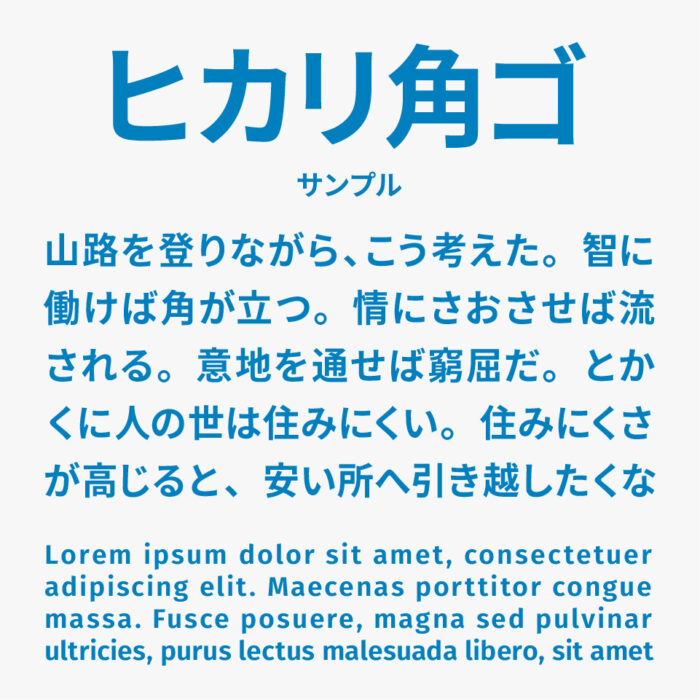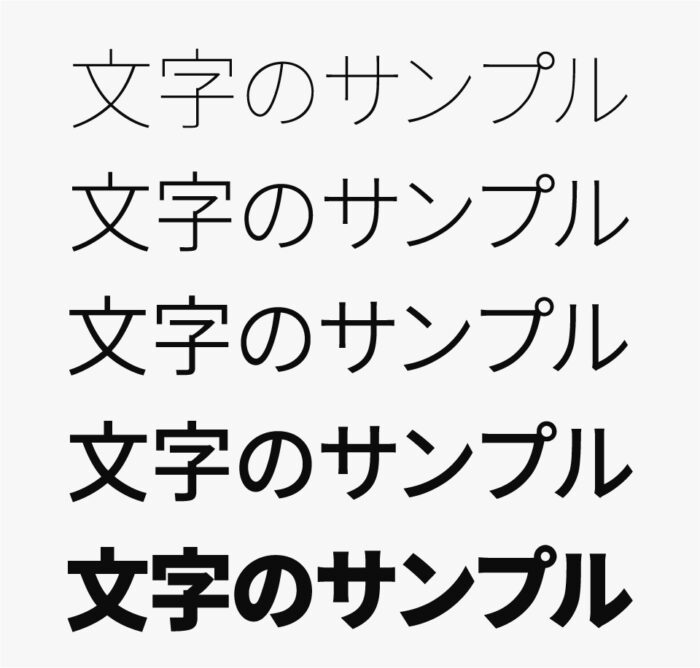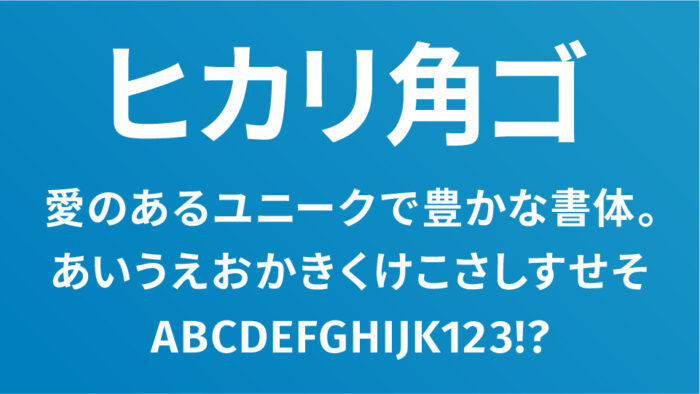
ヒカリ角ゴフォントは、源ノ角ゴシック(Noto sans)をベースとして、ふところを狭く、漢字をより平らかになるように調整されたゴシック体フォントです。
ベースとなっている源ノ角ゴシック(Noto sans)と比較してみると、わかりやすいですが、ヒカリ角ゴはフラットになるように漢字が調整されています。
また終筆部分を直角に平坦になっていることで、簡潔に見えるようになっています。
ウエイトも豊富で「Thin 100」、「Light 300」、「DemiLight 350」、「Regular 400」、「Medium 500」、「Bold 700」、「Black 900」の7種類のウエイトが用意されています。
収録文字は、ひらがな・カタカナ・英数字・記号・日常で使用する漢字はカバーされています。